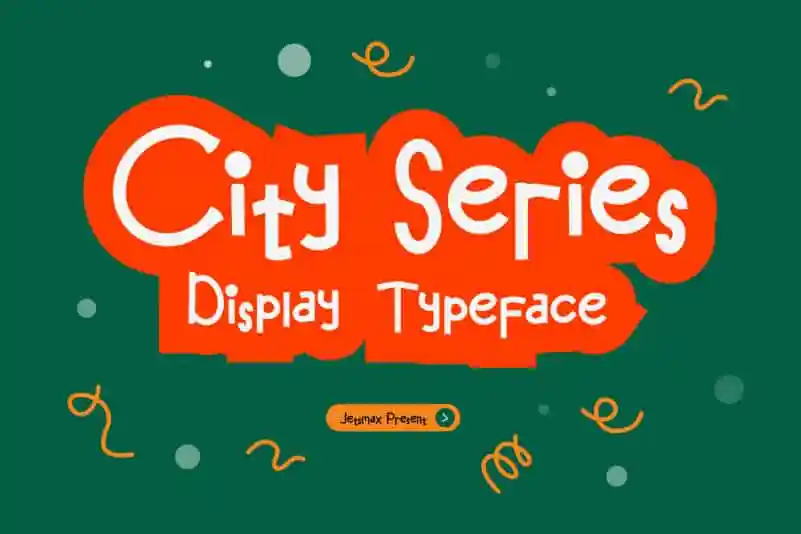
City Series Display Font – Download Grátis
A City Series Display Font foi inspirada no neveleiro, que é redondo e pontudo em alguns pontos específicos. Esta fonte captura a alegria do Natal, evocando um espírito de festa e criatividade para seus projetos únicos. Com linhas arredondadas e sutis bordas pontiagudas, essa família de fontes convida você a fazer trabalhos decorativos que se destaquem no seu projeto gráfico. Seja um card da árvore de Natal, uma embalagem personalizada ou qualquer outro elemento de arte, essa fonte trará uma atmosfera festiva para o seu trabalho. Jetsmax, designer responsável por City Series Display Font, oferece uma ferramenta poderosa para tornar seus projetos ainda mais especiais.